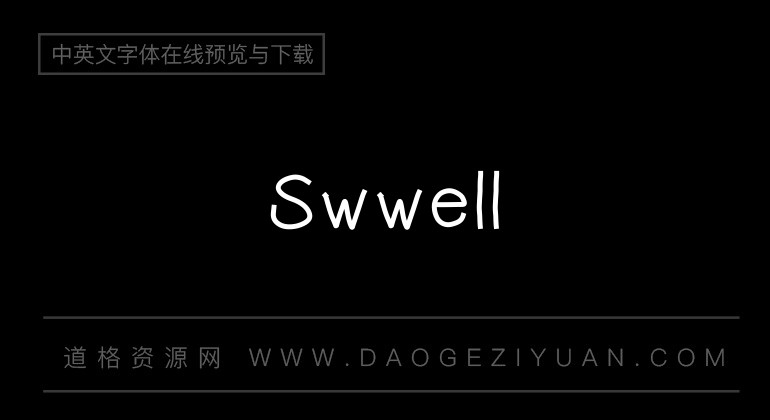
Swwell
Swell 是一款具有复古风格的字体,它具有温暖的感觉,比较适合用于标题、标语和特殊文本的设计。它的字体设计更加细腻、精致,具有自然的流动感,可以使文字更加清晰易读。Swell 字体也可以用于日常的文字设计,例如卡片、海报、宣传画等,可以让文字具有更好的可读性和视觉效果。
Swwell是一款非常不错的手写艺术字体,具有很好的视觉感,适合于文化类的宣传设计、商业类品牌的广告和产品包装设计以及个性化文字排版等较多场景。